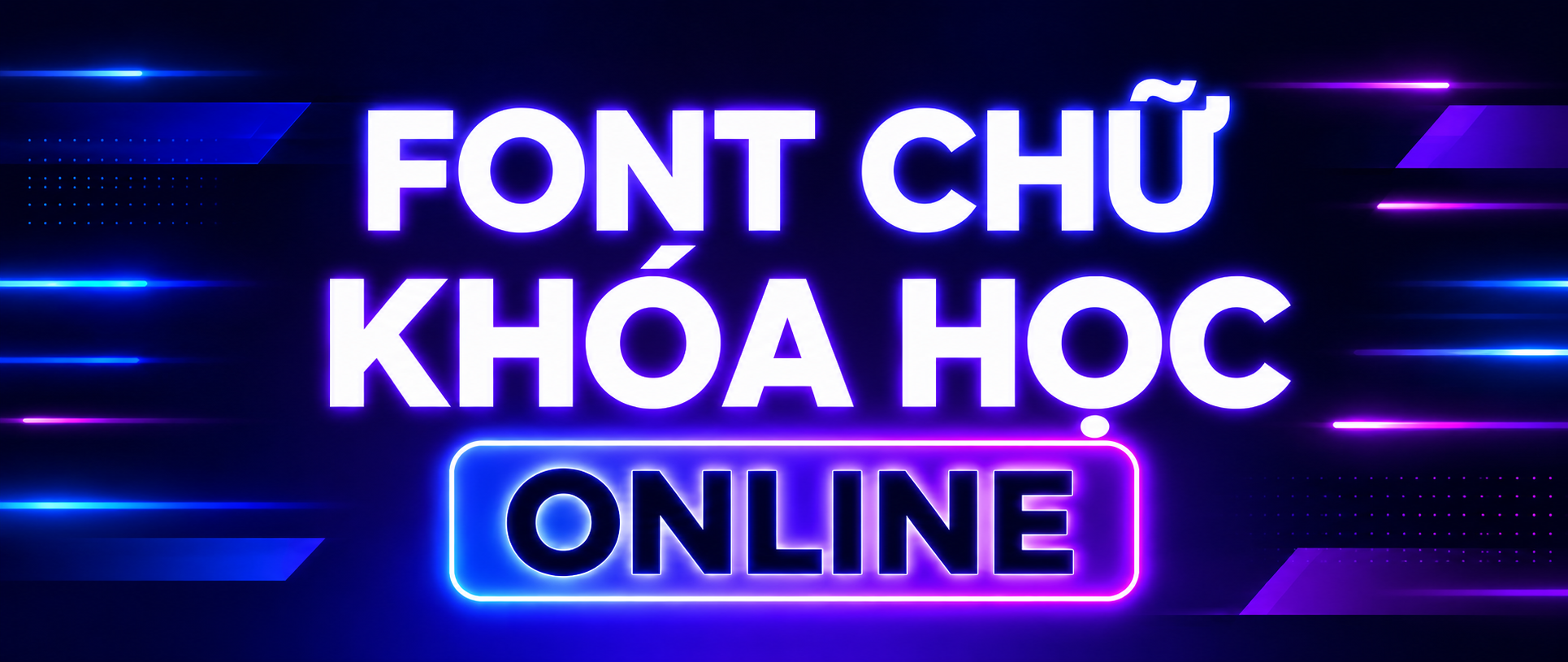
Khóa học online và webinar bán bằng niềm tin trước khi bán bằng nội dung. Người học nhìn thumbnail, landing page, banner quảng cáo, slide mở đầu hoặc chứng chỉ để đánh giá khóa học có chuyên nghiệp không. Vì vậy, font chữ khóa học online, webinar cần rõ, hiện đại, có cảm giác chuyên môn và hỗ trợ tiếng Việt tốt.
Bài viết này gợi ý các font Việt hóa trên Font S99 phù hợp cho khóa học AI, marketing, thiết kế, ngoại ngữ, tài chính, kỹ năng mềm, webinar bán hàng, workshop online, coaching và chương trình đào tạo nội bộ. Mỗi font được trình bày riêng một dòng với anchor Tải về để bạn dễ tải xuống và thử ngay vào thiết kế.
Trong giáo dục online, font không chỉ để trang trí. Font quyết định người xem có đọc được tiêu đề khóa học, hiểu lợi ích, thấy rõ CTA và cảm nhận được mức độ chuyên nghiệp của giảng viên hay không. Một font quá vui có thể làm khóa học thiếu nghiêm túc; một font quá khô lại làm landing page mất sức hút.
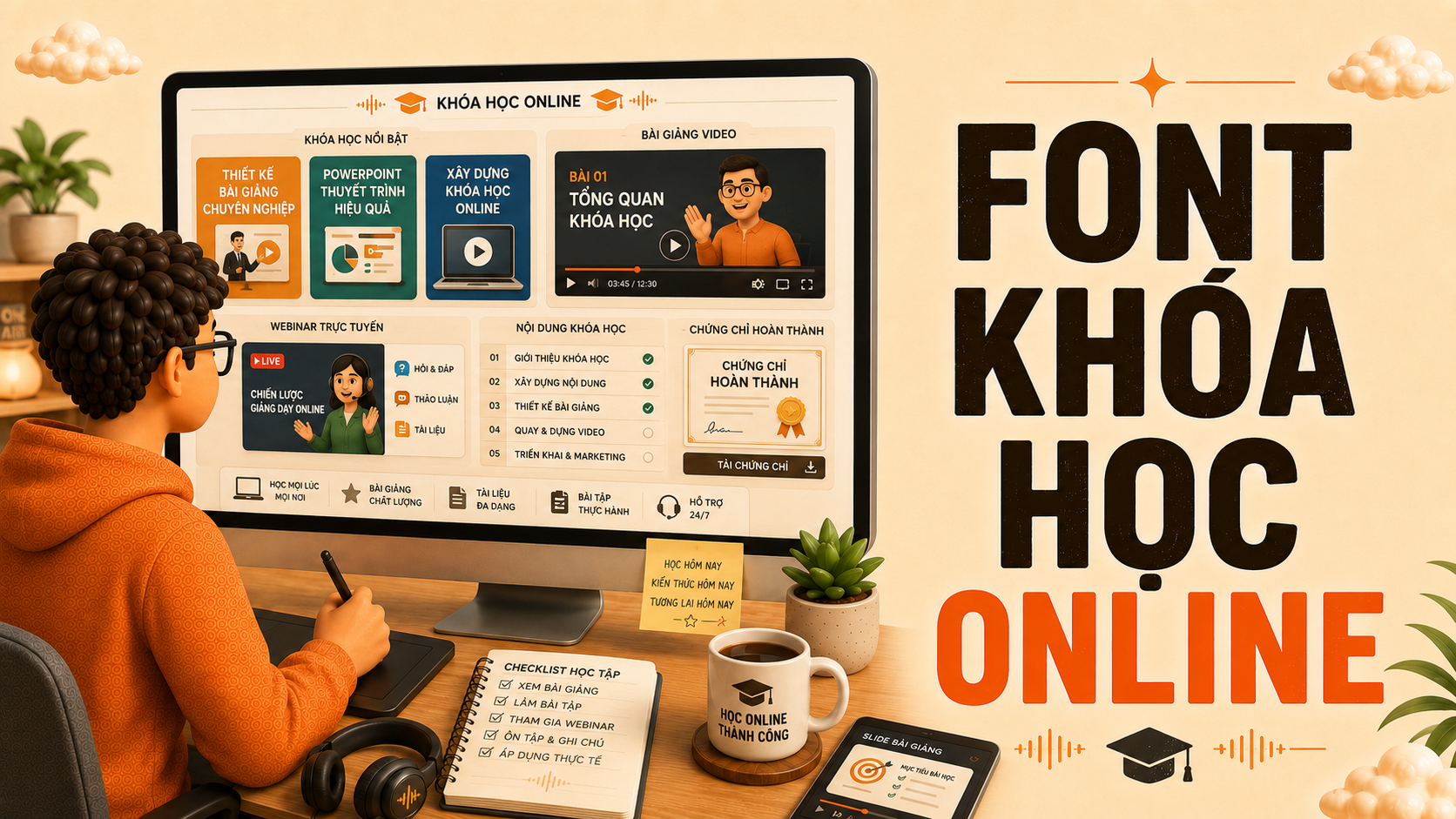
Khóa học online thường có nhiều lớp thông tin: tên khóa học, mô tả kết quả, tên giảng viên, lịch học, giá, ưu đãi, số buổi, chứng nhận và nút đăng ký. Vì vậy, cần phối font theo vai trò. Headline có thể mạnh hơn, nhưng phần nội dung và CTA phải thật rõ.
Với tiếng Việt, font Việt hóa là điều bắt buộc. Các cụm như khóa học trực tuyến, làm chủ AI, học thiết kế, xây dựng thương hiệu, đăng ký ngay, nhận tài liệu miễn phí có nhiều dấu. Font lỗi dấu sẽ làm banner hoặc slide nhìn kém tin cậy.
Người học thường nhìn quảng cáo trên điện thoại. Font cần đọc được khi thumbnail bị thu nhỏ, đặc biệt với các cụm như miễn phí, khai giảng, học thử, ưu đãi, chứng chỉ. Nếu chữ chỉ đẹp ở bản thiết kế lớn nhưng mờ trên mobile, không nên dùng làm font chính.
Khóa học công nghệ cần font gọn, hiện đại. Khóa học kinh doanh cần rõ và chuyên nghiệp. Khóa học sáng tạo có thể dùng font cá tính hơn. Webinar bán hàng cần font mạnh ở CTA. Khóa học trẻ em hoặc kỹ năng mềm có thể mềm hơn nhưng vẫn phải dễ đọc.
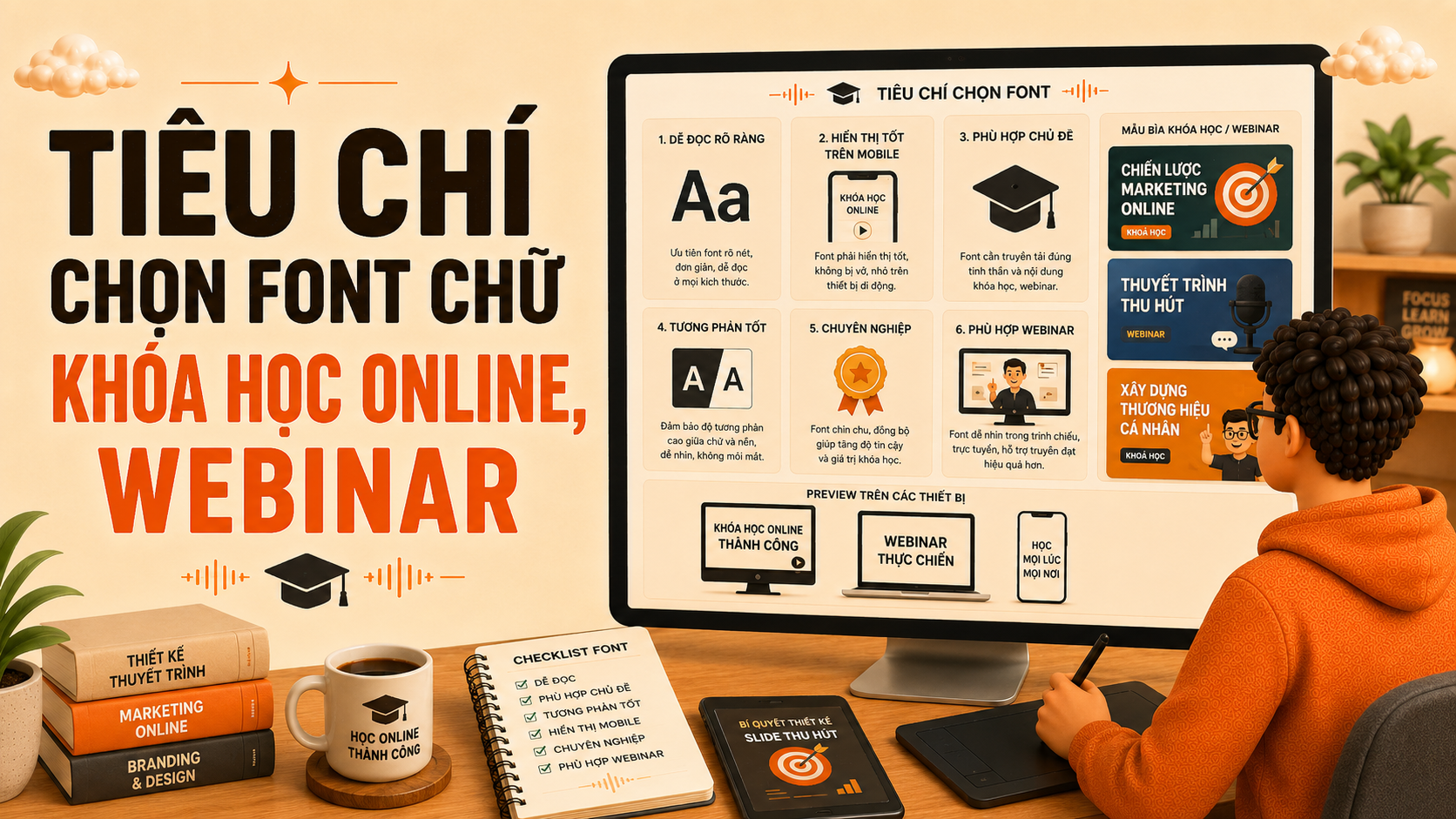
Một khóa học thường có nhiều asset: landing page, cover bài học, slide, workbook, certificate, email banner, social post. Font nên đủ ổn định để dùng xuyên suốt, tránh mỗi bài giảng một kiểu chữ.
Hãy thử font với những cụm có dấu dày như khóa học, kỹ năng, chuyên sâu, thực chiến, chứng nhận, hướng dẫn, nền tảng, chuyển đổi số. Nếu dấu bị lệch, nên đổi font trước khi triển khai toàn bộ chiến dịch.
Thumbnail và banner quảng cáo cần kéo mắt nhanh. Nhóm font display mạnh phù hợp với khóa học công nghệ, AI, marketing, bán hàng, tài chính, webinar launch sản phẩm hoặc các buổi workshop cần tạo cảm giác hành động.
Hãy dùng nhóm này cho headline ngắn như Làm chủ AI, Webinar miễn phí, Tăng doanh số, Học thiết kế từ đầu, Ứng dụng ChatGPT, Khai giảng tháng này. Phần mô tả dài, tên giảng viên và thời gian nên dùng font phụ rõ hơn.
Sans-serif là nhóm font nền quan trọng nhất cho khóa học online. Landing page có nhiều đoạn giải thích, bullet lợi ích, lịch học, bảng giá, feedback học viên và CTA. Slide bài giảng cũng cần font đọc tốt trong thời gian dài.
Nhóm này phù hợp cho nội dung chính, mô tả module, checklist, workbook, email, tài liệu PDF và giao diện học. Dùng weight semibold cho tiêu đề phụ, regular cho mô tả và bold cho CTA để giữ nhịp đọc rõ ràng.
Các khóa học cao cấp, chương trình coaching, masterclass, đào tạo lãnh đạo hoặc chứng chỉ cần cảm giác uy tín hơn. Khi đó, font sang và thanh lịch giúp thiết kế nhìn có chiều sâu, nhất là trên certificate, cover ebook và trang giới thiệu giảng viên.
Font TH Luxury 8 - Tải về
Font TH Cameo Sans - Tải về
Font TH Selvia Genatu - Tải về
Font TH Wrigskan - Tải về
Font Playfair Display Việt hóa - Tải về
Nên dùng nhóm này cho logo khóa học, headline masterclass, tên chứng chỉ, bìa workbook hoặc quote của giảng viên. Phần nội dung chi tiết vẫn nên phối với sans-serif rõ để tránh cảm giác khó đọc..
Công thức 1 là display mạnh plus sans-serif. Dùng font mạnh cho thumbnail, banner ads và headline webinar; dùng sans-serif cho landing page, nội dung slide, lịch học và CTA. Công thức này hợp khóa học công nghệ, AI, marketing và bán hàng.
Công thức 2 là luxury font plus sans-serif. Dùng font sang cho masterclass, chứng chỉ, coaching hoặc khóa học chuyên gia; dùng sans-serif cho mô tả chương trình và thông tin đăng ký.
Công thức 3 là font thân thiện plus sans-serif. Dùng font mềm cho khóa học trẻ em, kỹ năng mềm, workshop cộng đồng; dùng sans-serif cho phần thông tin cần đọc nhanh.
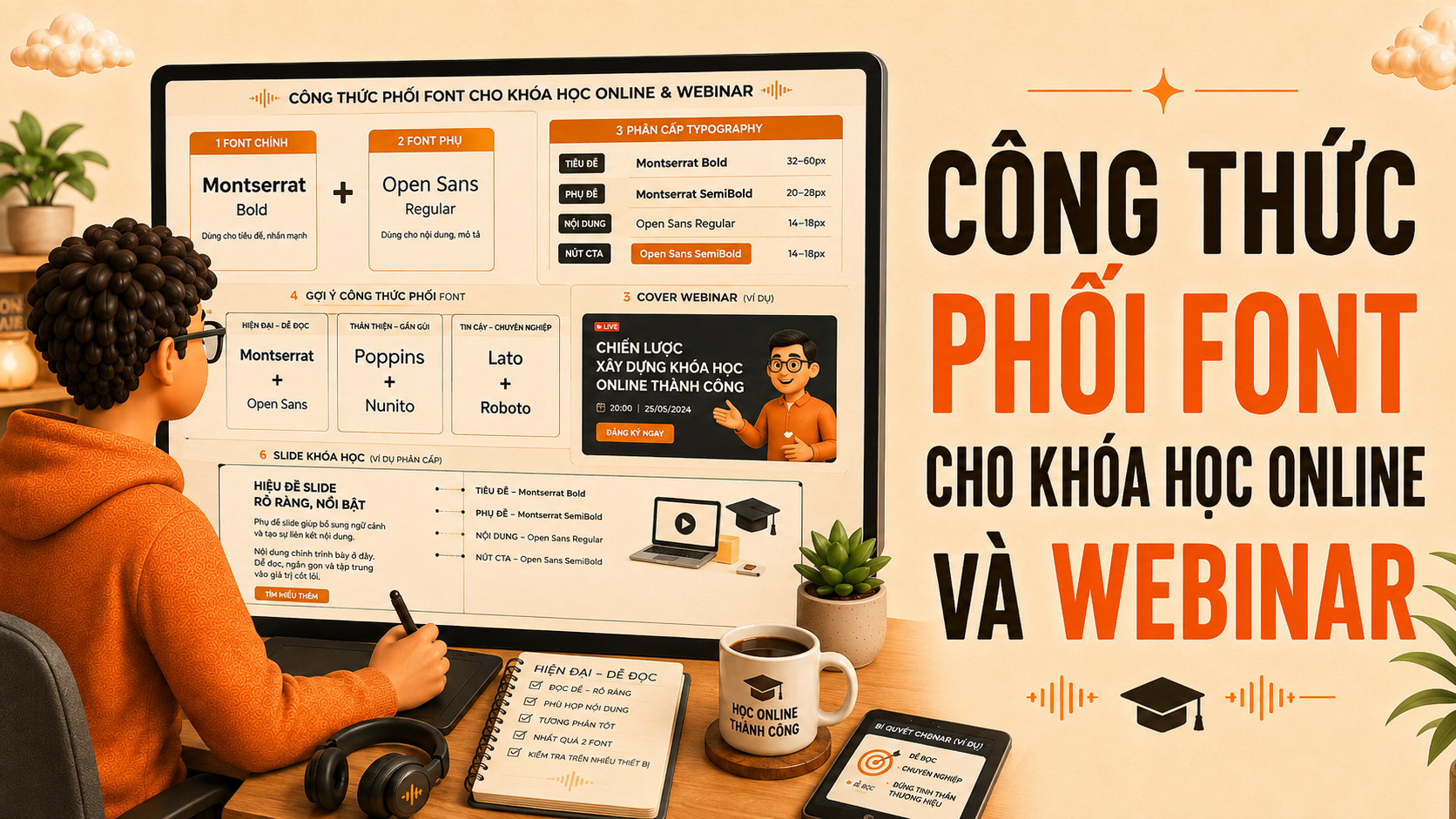
Đừng dùng quá nhiều font trong cùng một hệ thống. Với khóa học online, 2 font là đủ trong đa số trường hợp. Nếu cần font thứ ba, chỉ dùng cho sticker như miễn phí, early bird, bonus hoặc live webinar.
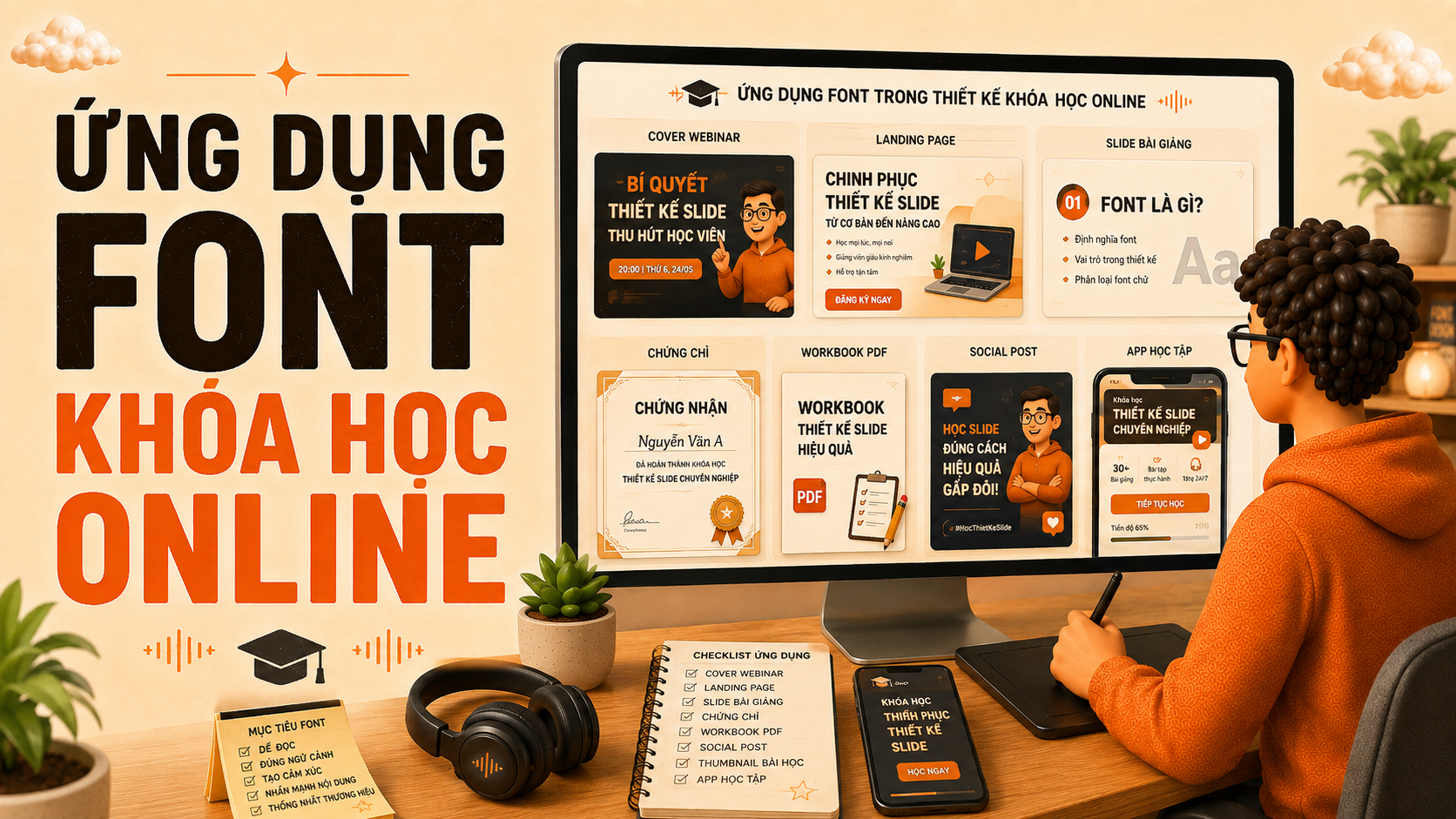
Font chữ khóa học online, webinar tốt phải giúp người xem đọc nhanh, tin tưởng và muốn bấm đăng ký. Hãy dùng font mạnh cho thumbnail, sans-serif cho landing page và slide, font sang cho masterclass hoặc chứng chỉ, font thân thiện cho khóa học trẻ em và cộng đồng.